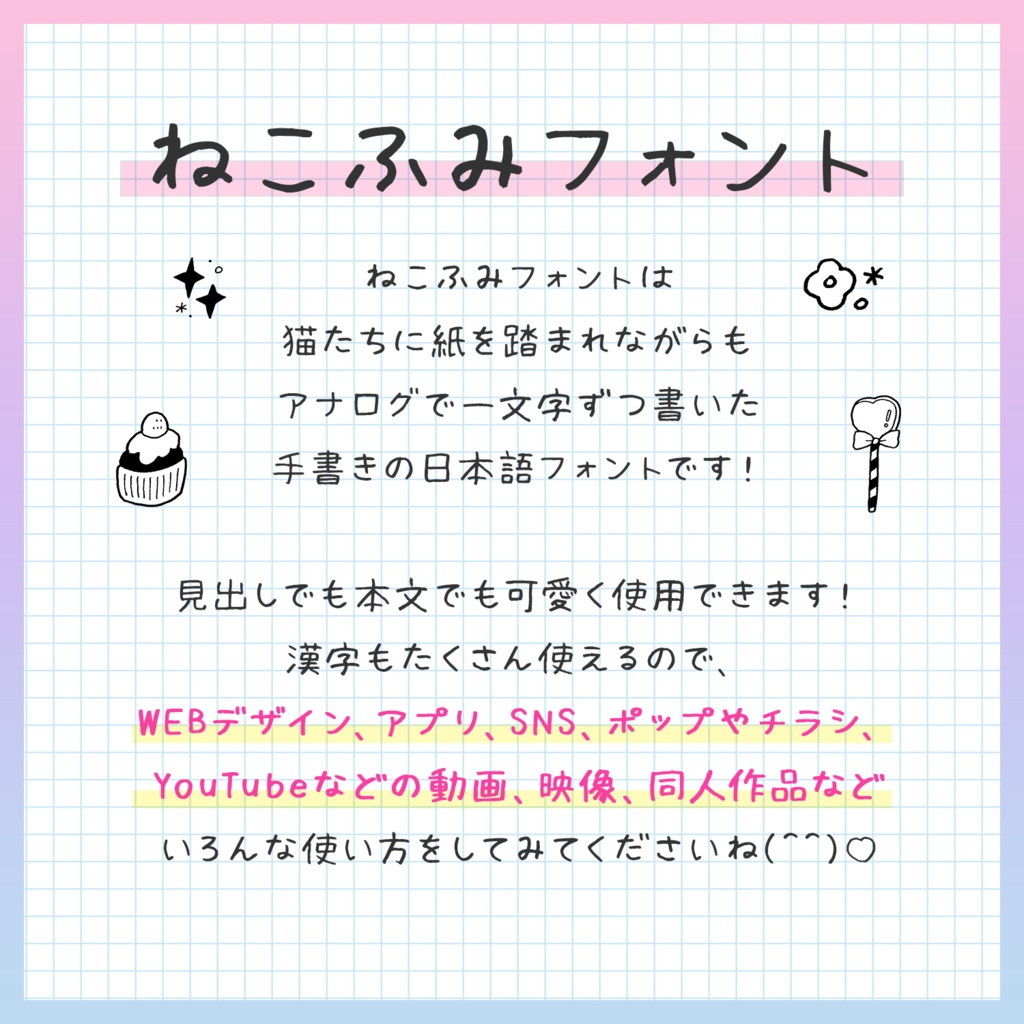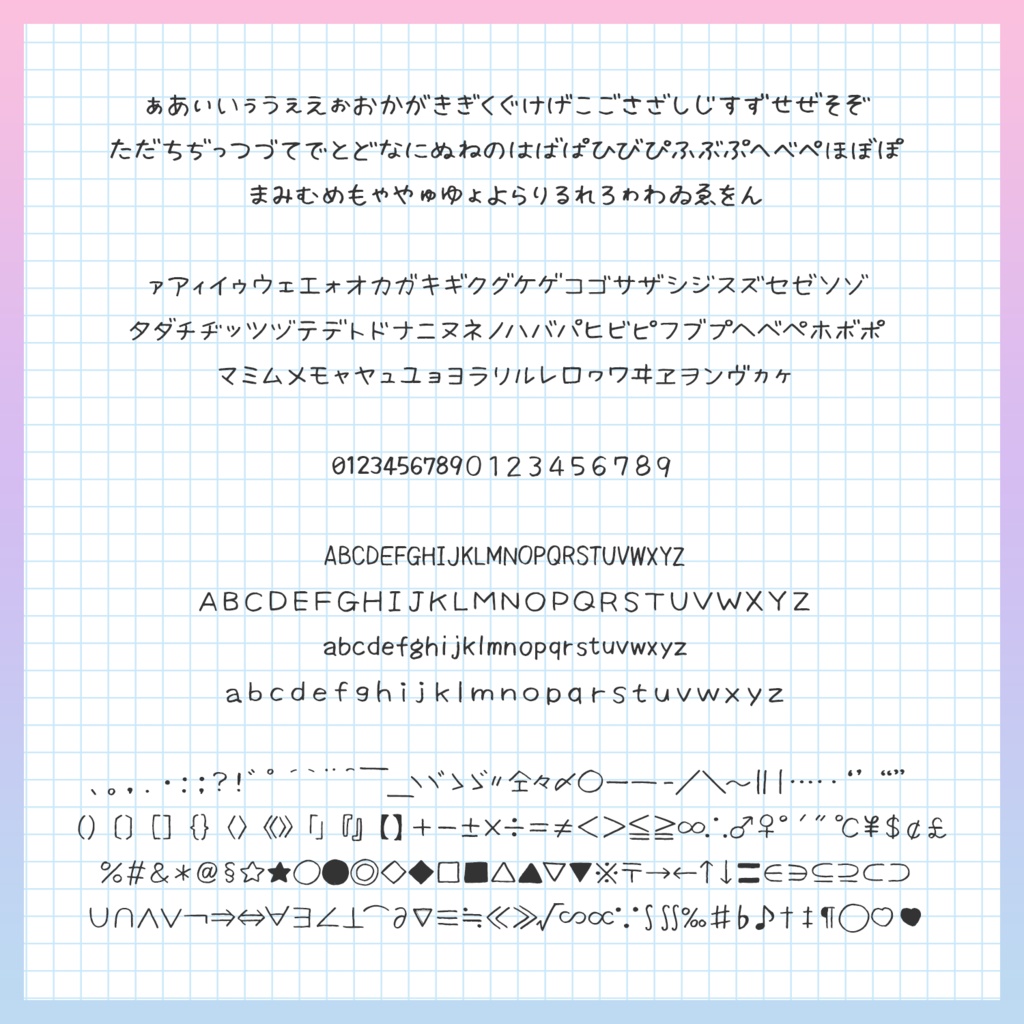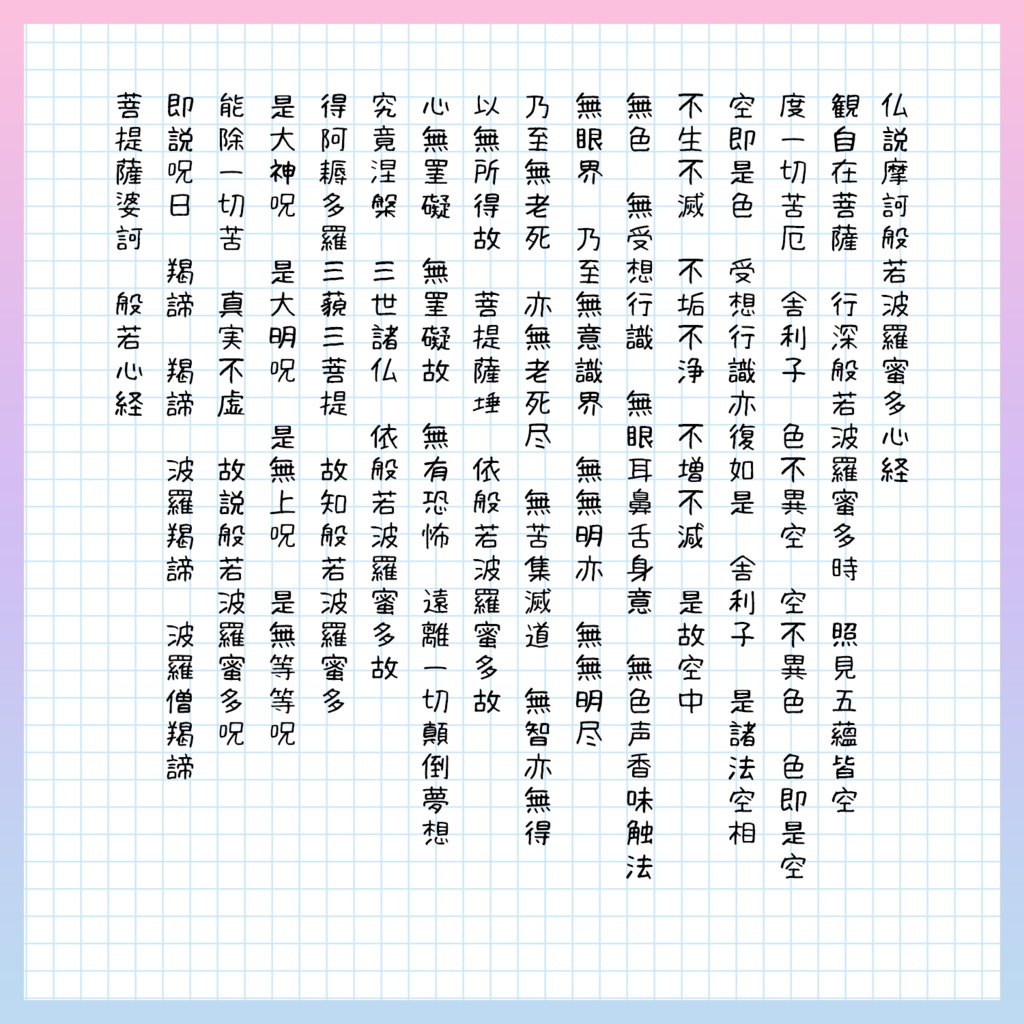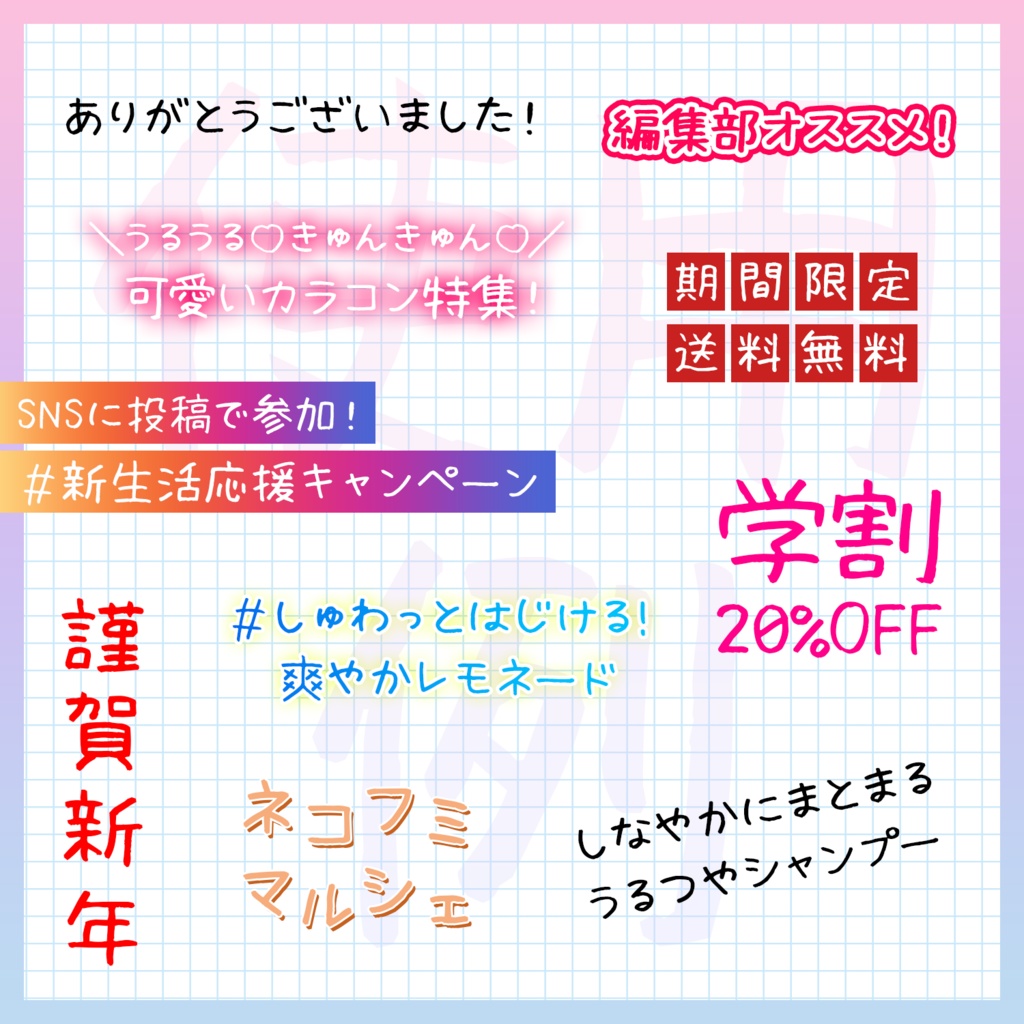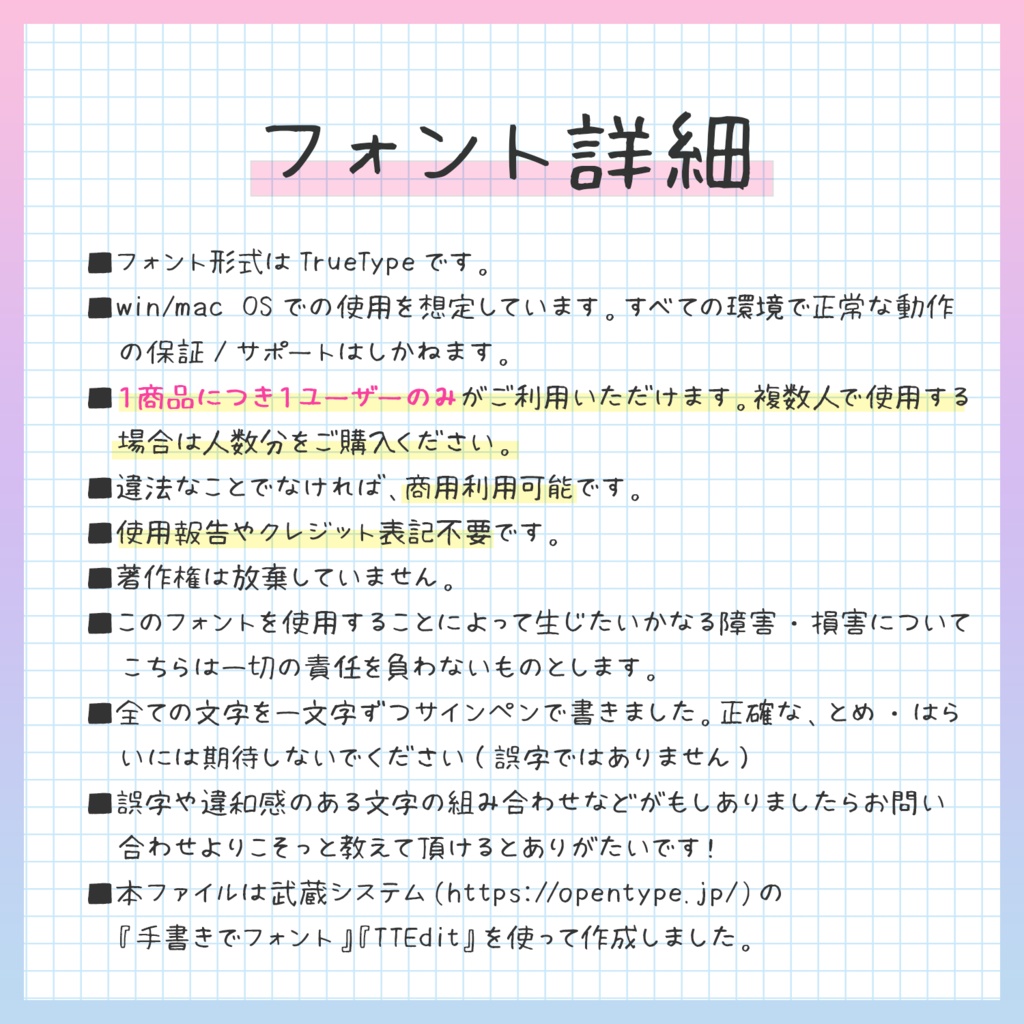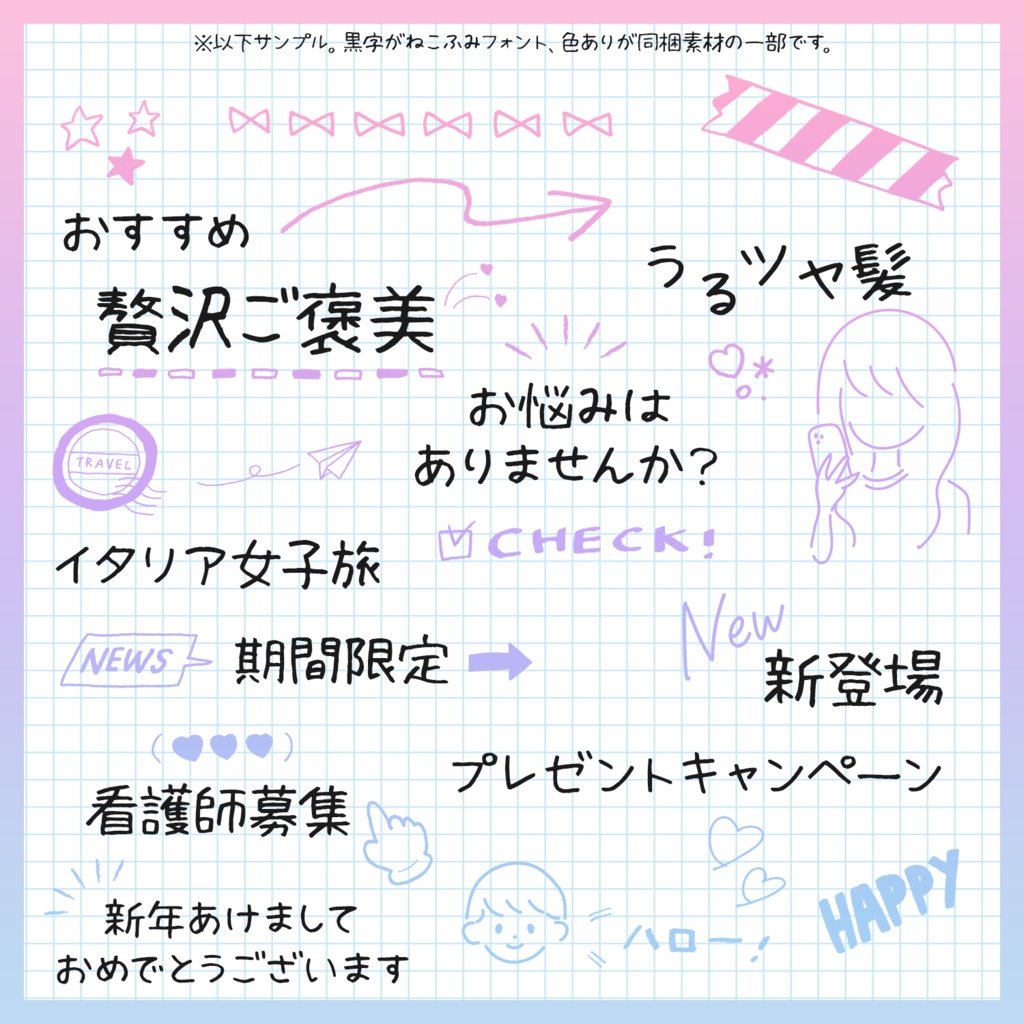
ねこふみフォントは、猫たちに紙を踏まれながらも アナログで一文字ずつ書いた手書きの日本語フォントです! 見出しでも本文でも可愛く使用できます! 漢字もたくさん使えるので、 WEBデザイン、アプリ、SNS、ポップやチラシ、 YouTubeなどの動画、映像、同人作品など いろんな使い方をしてみてくださいね(^^)♡
【全7456文字】 ひらがな/全角カタカナ/半角カタカナ 全角英数/半角英数/記号 第一水準/第二水準/拡張漢字 ギリシャ文字/ロシア文字 +ハートマーク(2種類)、波ダッシュ(〜) ごく一部の第三水準漢字を収録! 難しい苗字や、般若心経も打てます!!